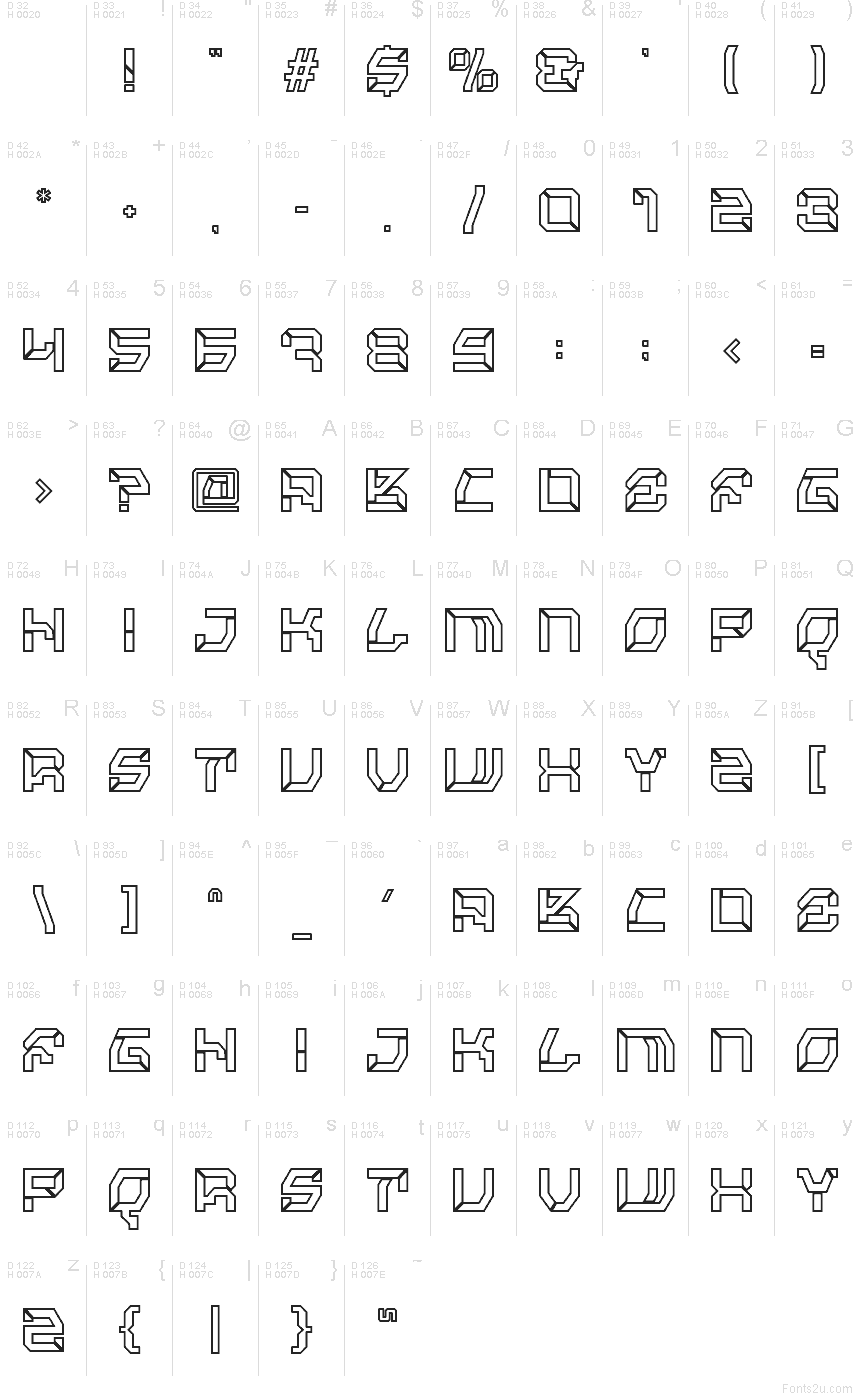
يعد خط Spectra Volt Three من Putracetol Studio خط عرض مستقبلياً مجانياً، يتميز بظلال حادة ومشطوفة ومخطط مقسم يجعل كل حرف يبدو كأنه مقصوص من ألواح مطوية. يمنح هذا التعامل المتكرر مع الحواف التصميم إيقاعاً ميكانيكياً قوياً، حيث تلعب الزوايا والوصلات القطرية دوراً بصرياً أكبر من سماكة الخط نفسها.
إنه خيار مثالي لعناوين الألعاب، وملصقات الخيال العلمي، ورسومات الفعاليات التقنية، والصور المصغرة على يوتيوب، وهويات العلامات التجارية للملابس، حيث قد يبدو الخط الهندسي العادي محايداً أكثر من اللازم. بفضل هيكله المحدد، تظهر الكلمات القصيرة بشكل حيوي وجرافيكي، مما يجعله مثالياً للاستخدام في الشعارات، وعناوين الأقسام، أو تفاصيل التغليف دون الحاجة إلى مؤثرات إضافية.
Spectra Volt Three